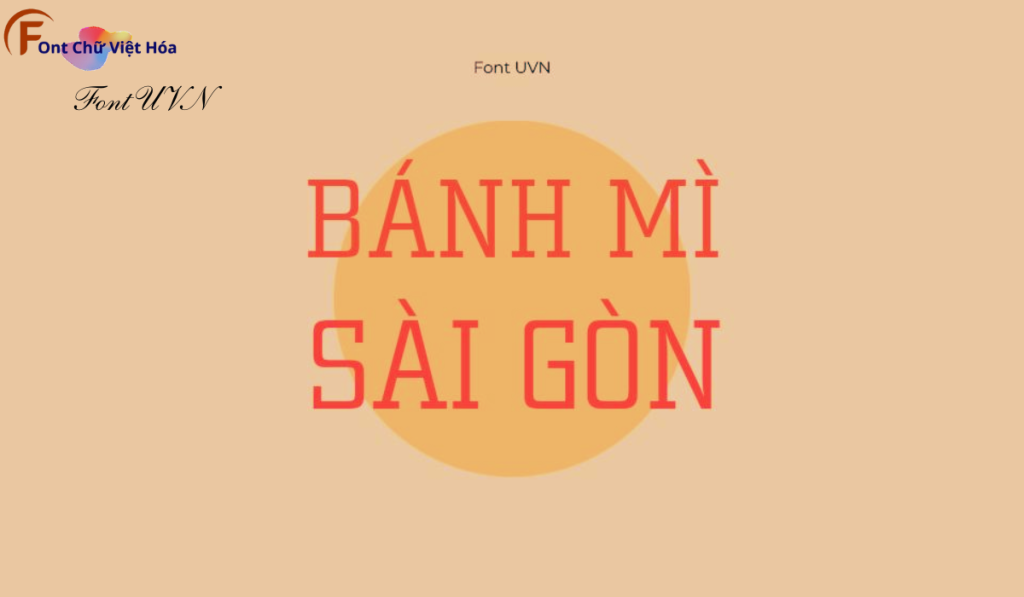
Font UVN Thành Phố Việt Hóa
Tác giả: UVN Thành Phố Việt Hóa
Bộ Font: UVN
Phân loại: Cá tính, Độc đáo
Kiểu chữ: Có chân
Độ dày: Mỏng, Vừa, Đậm
Font UVN Thành Phố Việt Hóa là một font chữ có chân hiện đại, thuộc bộ font UVN. Được thiết kế với mục tiêu mang lại sự tinh tế và thanh lịch, font này phù hợp cho các dự án thiết kế như website, tài liệu, và bao bì sản phẩm. Với các nét chữ rõ ràng và độ dày đều đặn, Font UVN Thành Phố Việt Hóa không chỉ dễ đọc mà còn tạo cảm giác chuyên nghiệp. Việc Việt hóa font giúp người dùng dễ dàng sử dụng trong các thiết kế tiếng Việt, mang lại sự tiện lợi và thẩm mỹ cao.